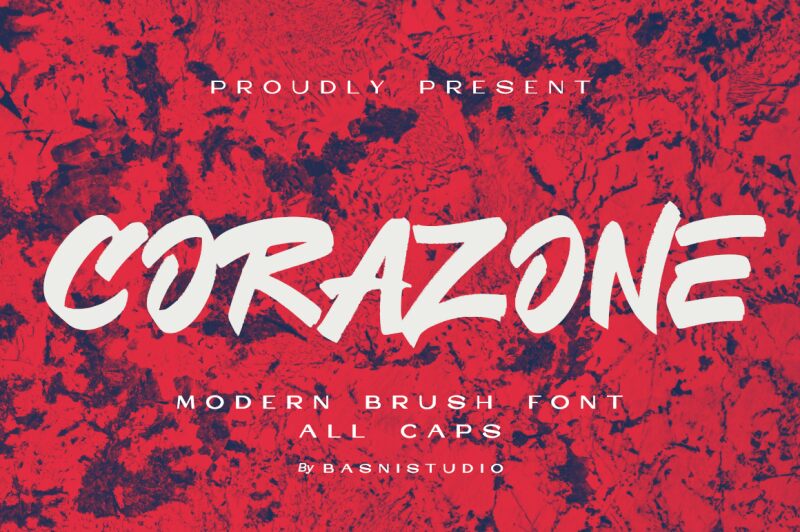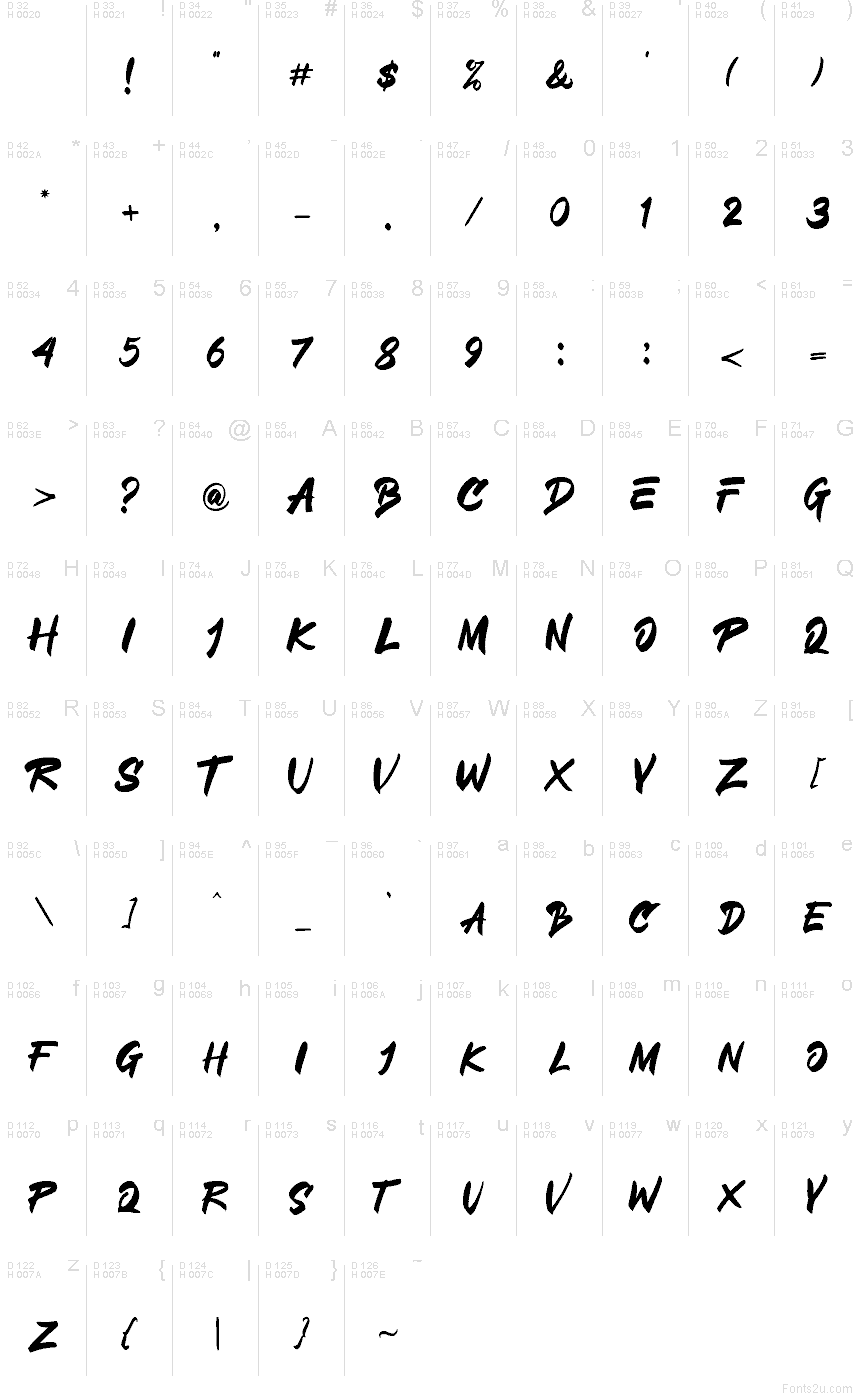
CORAZONE
Corazone от Basnistudio — это бесплатный акцидентный шрифт в стиле brush, с дерзкими, рублеными заглавными буквами и непринужденным настроением вывесок, написанных от руки. Буквы варьируются от широких, насыщенных чернилами кривых до острых, крючковатых окончаний, что придает всему шрифту быструю, энергичную подачу, больше напоминающую мурал, чем аккуратную каллиграфию.
Он отлично подходит для заголовков плакатов, музыкального оформления, спортивного брендинга, упаковки кофе и титров, где короткой фразе нужен этот необработанный, «малярный» эффект. Будучи бесплатным шрифтом, CORAZONE лучше всего работает в крупных, эффектных форматах, особенно на обложках и в набросках логотипов, поскольку заглавные буквы передают движение и напор в каждом штрихе.